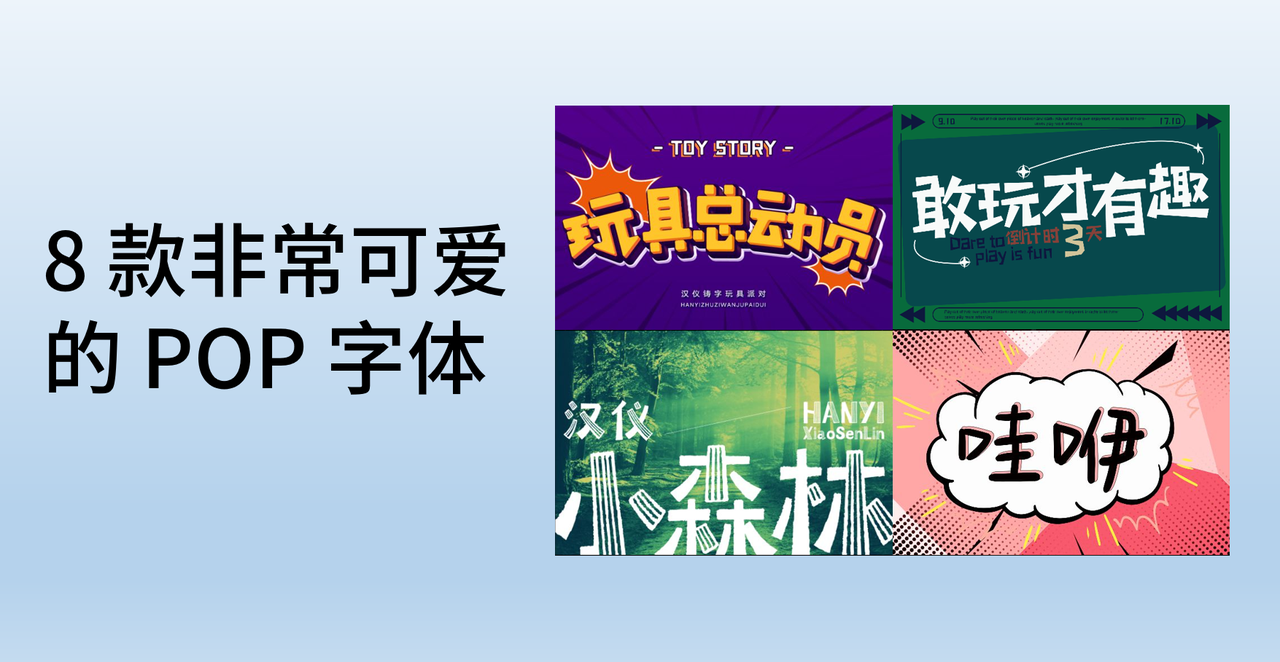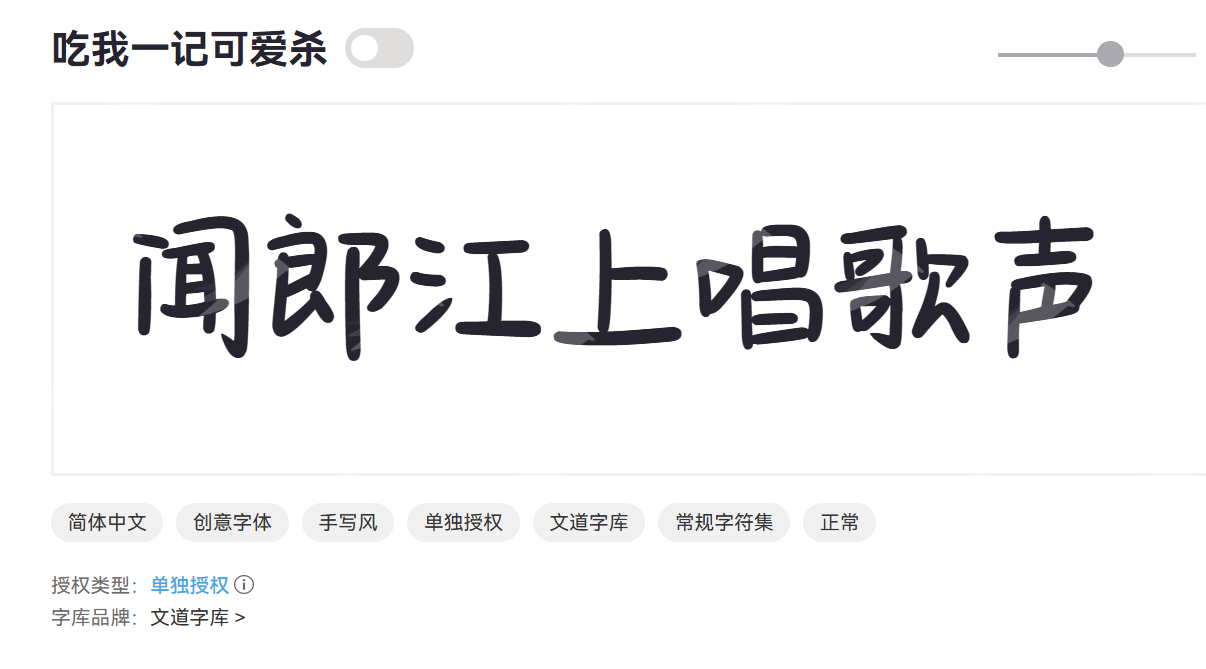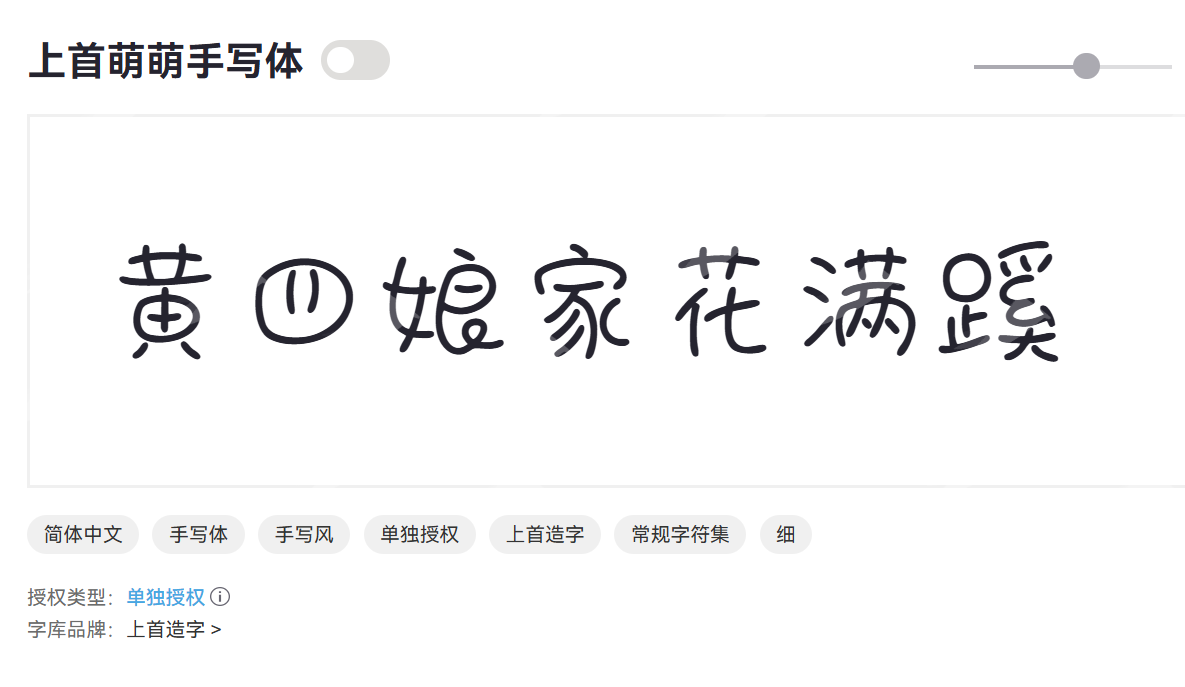
POP 字体大全,分享 8 款非常可爱的 POP 字体
说到 POP 字体,你可能第一时间想到的是商店里那些色彩鲜艳、吸引眼球的促销海报,或者是各种活动宣传单上充满活力的标题。都没错,我是非常喜欢这种“可爱”的字体,今天就给大家推荐 8 款我自己比较喜欢的 POP 字体。大家也喜欢的,在文末有具体的获取方式。
POP字体是什么样的字体?
“POP”这个词,其实来源于“Popular”,意为“流行的”、“大众的”。而POP字体,就是一种为了吸引大众注意力而设计的字体。在商业广告和海报设计领域,为了在琳琅满目的信息中迅速抓住消费者的眼球,设计师们开始尝试各种新颖、醒目的字体形式。
POP字体的优势
- 视觉冲击力强: 这是POP字体最核心的优势。它通常拥有粗壮的笔画、夸张的字形、鲜明的轮廓,甚至会加入一些阴影、渐变、描边等装饰效果,使得文字本身就具有极强的视觉吸引力。
- 个性十足: POP字体不像宋体、黑体那样严谨、中规中矩,它更富有表情。不同的POP字体可以传达不同的情绪。设计师可以通过选择合适的POP字体,为作品注入鲜活的情感和独特的个性。
- 场景适应性广: 虽然很多人将POP字体与促销海报划等号,但它的应用范围远不止于此。产品包装、活动宣传、社交媒体封面、游戏界面等都可以使用 POP 字体。
- 信息传递高效: 尽管POP字体可能在字形上有所变化,但其核心目的是为了清晰地传递信息。
8 款 POP 字体分享
默陌纸飞机体
默陌纸飞机体是一款卡通手绘风格字体,融入纸飞机意象,通过几何造型与涂绘笔触设计。
默陌纸飞机体卡通味浓厚,趣味性强、可爱而不幼稚,辨识度高。适合制作儿童品牌包装、卡通海报、趣味文创产品、社交媒体标题、幼教素材等。
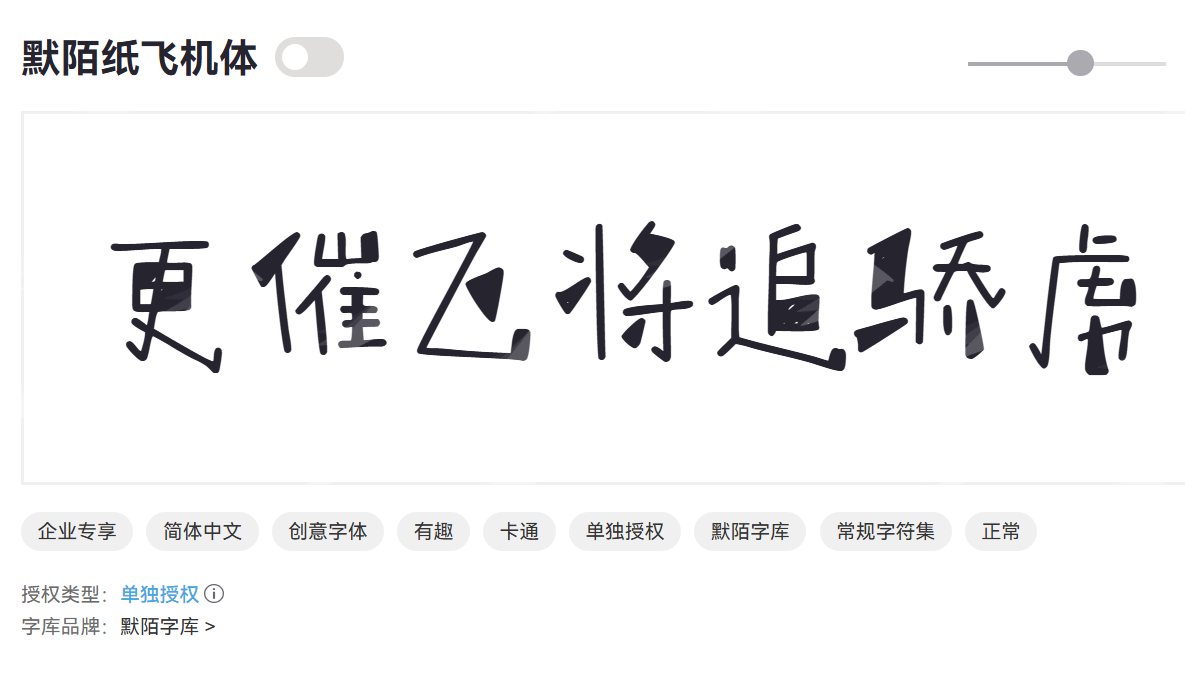
吃我一记可爱杀
吃我一记可爱杀是由文道字库出品的一款软萌手写风格字体,名称自带趣味属性。
吃我一记可爱杀笔画粗厚有力,软萌又带俏皮感,适合少女心产品包装、甜品店招牌等场景。
上首萌萌手写体
汉仪铸字蒸汽朋克
汉仪铸字蒸汽朋克是汉仪字库出品的创意艺术字体,融合蒸汽朋克与工业复古风格。使用场景包含科幻游戏海报、蒸汽朋克主题活动、潮牌服饰包装、科技感品牌宣传、电子音乐专辑封面等。
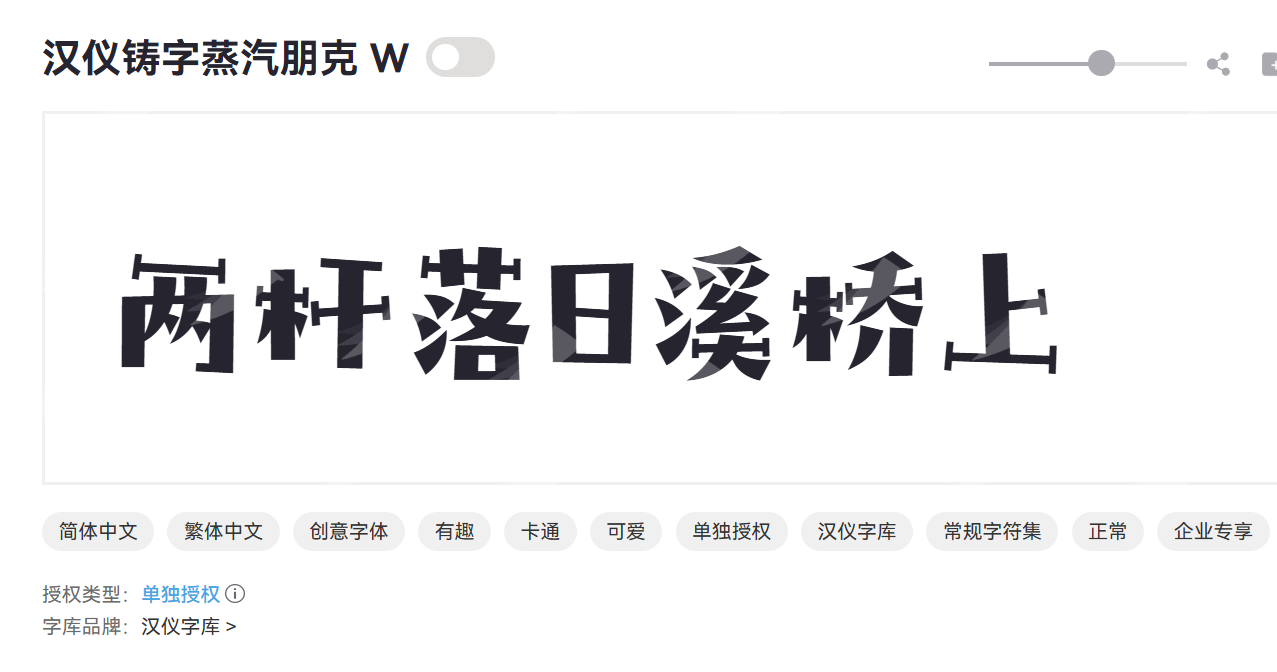
汉仪小森林
汉仪小森林是汉仪字库设计的自然主题艺术字体,笔画自带树木纹理感。自然清新、独特性强,兼具力量与可爱,质感突出。
汉仪小森林适合森林系文创产品、户外品牌包装、生态主题海报、治愈系书籍封面等场景。
三极玩酷简体
三极玩酷简体是一款潮流年轻化的简体字体,强调玩味与酷感。结构大胆、设计前卫、年轻潮流气息浓,所以它非常适合街头潮牌、潮流电商标题、嘻哈音乐封面、街舞活动宣传等设计场景。
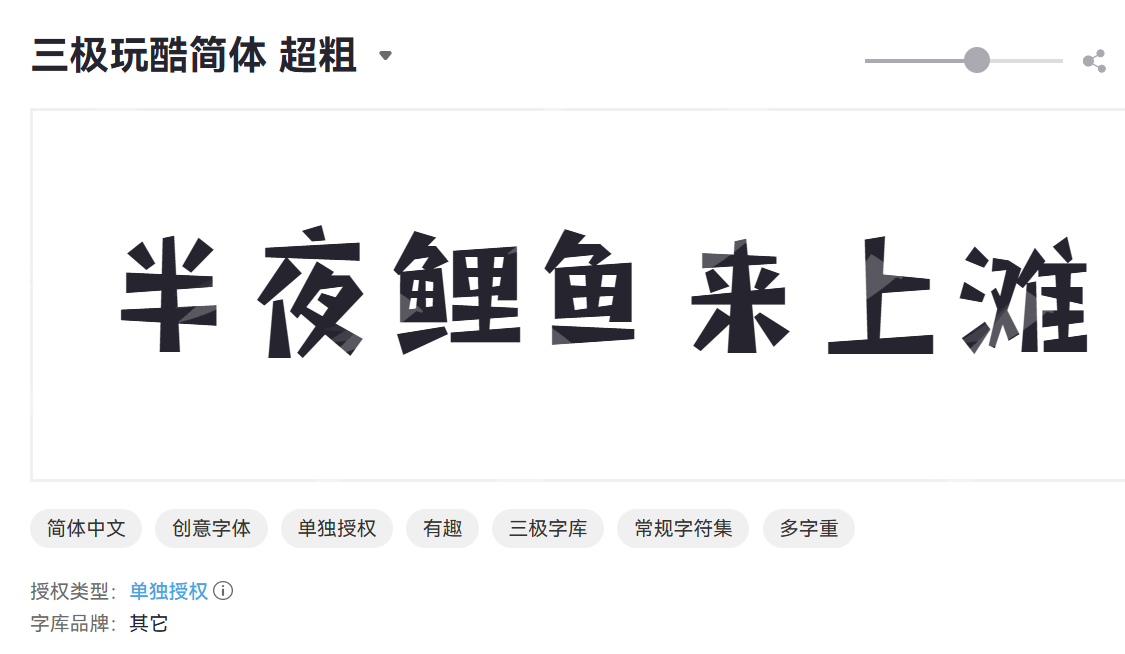
汉仪铸字玩具派对
汉仪铸字玩具派对是汉仪出品的欢乐玩具风格字体,充满童趣与派对氛围。字形圆润饱满,活泼跳跃感强,适合营造节日气氛。比如:派对活动海报、生日主题设计、亲子品牌宣传、节日文创产品。
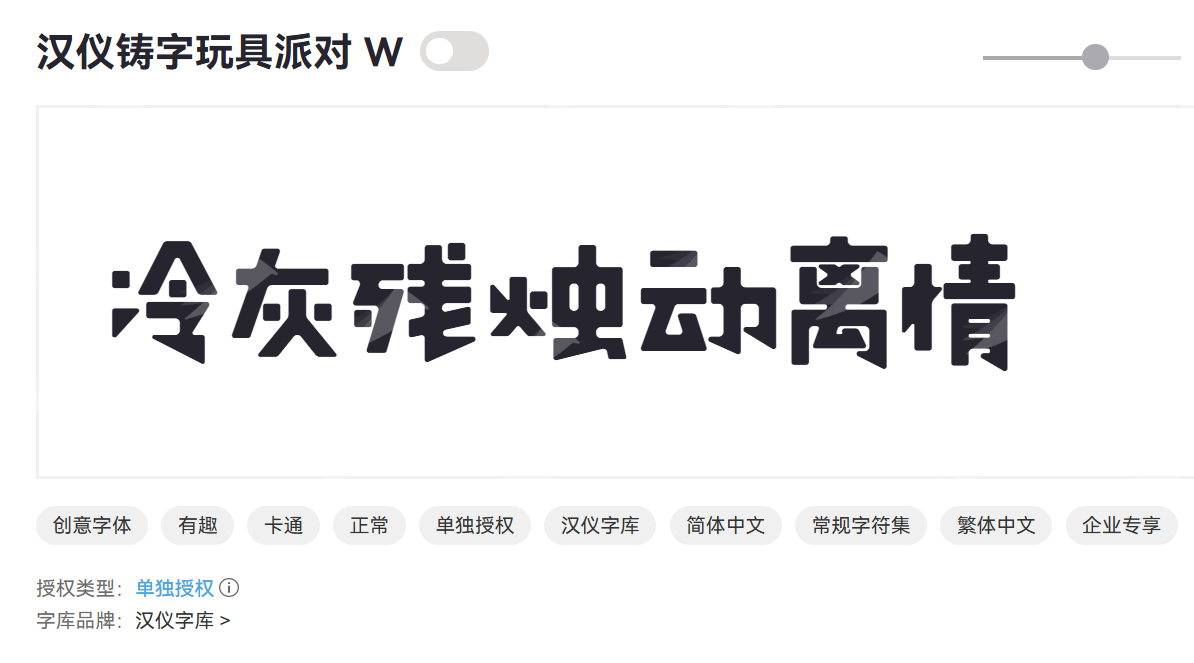
汉仪悠然体
汉仪悠然体是一款轻松闲适的现代中文字体,笔画流畅自然、结构放松,阅读舒适度高、适合长时间阅读场景。比如海报文案、书籍内文、咖啡厅菜单、轻奢产品介绍等等。